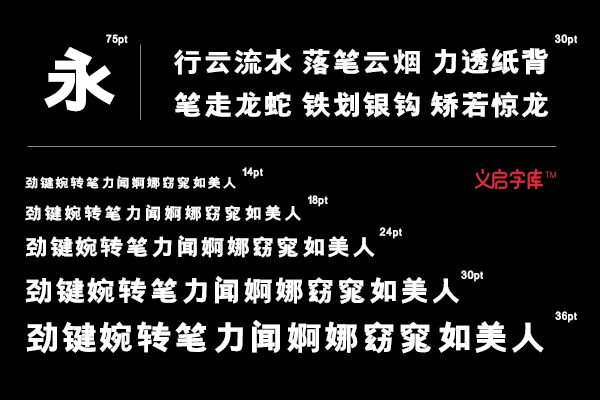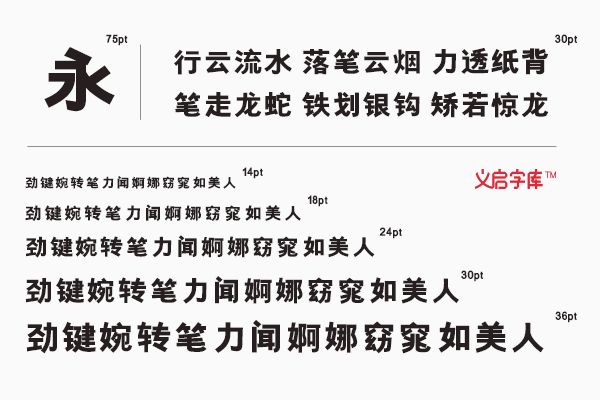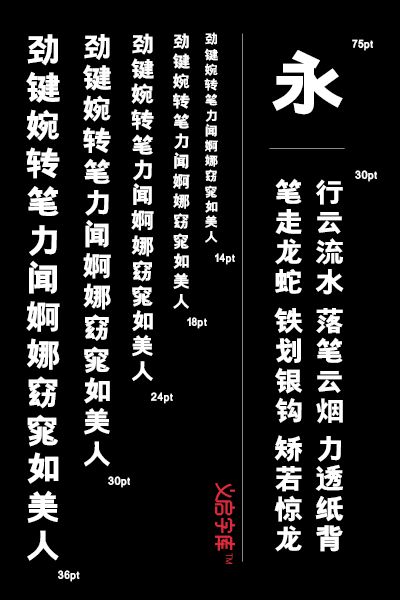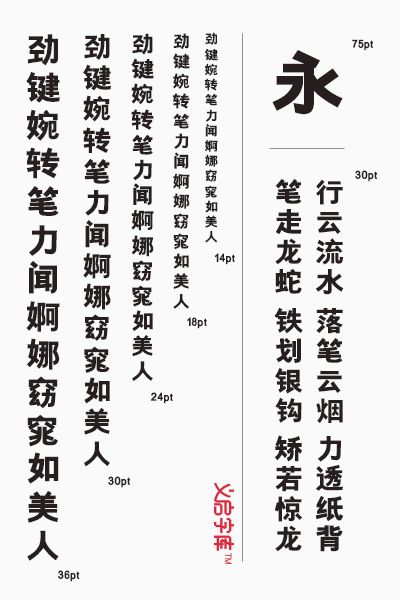
义启粗黑字体,能够助你走上成功之路的个性字体设计概念字体,现已更名为包图粗黑体。
小A是一个公司的设计师,有一次他接到一个任务——设计一个广告。由于甲方是准备上市的公司,所以此次无论对甲方还是乙方都是一个巨大的挑战,小A夜以继日的加班多想出几个方案。
“设计师,我想把这里换成长颈鹿图案。”“设计师,我想把这里改成圆形。”经过甲方的一再要求,A也一再更改。最终历时五个星期定初稿。
“叮咚”黑夜中的微信消息提醒打破了小A的美梦。原来是甲方发来的微信并要求改广告字体,觉得字体老土难看,不符合公司品牌形象。敬业的小A,无怨无悔的打开电脑开始地毯式搜索、筛选。
他发现义启粗黑体非常符合甲方的要求。该字体使用的是粗黑体,横撇竖捺大小一致,方方正正,非常醒目,能吸引人的眼球。另外,该字体方头方尾,起笔和落笔都切平,加粗了的黑体字,给人一种温暖憨厚的感觉,就像大家喜爱的大白。
最后小A更改成义启粗黑体,客户看后非常满意,称赞小A的专业精神和独到的眼光,同时客户也被义启粗黑体大为吸引,方案最终定了。 小A帮公司完美的解决客户问题,他的认真努力工作,老板都看在眼里。最后小A还升职加薪了。
左右结构均匀的义启粗黑体,时尚还简约,不仅适用于广告、屏显、LOGO,还非常适用于年轻的群体。成熟稳重的它,你不要错过。